한글 타이포그래피에서 폰트 크기 기준 제대로 잡는 방법
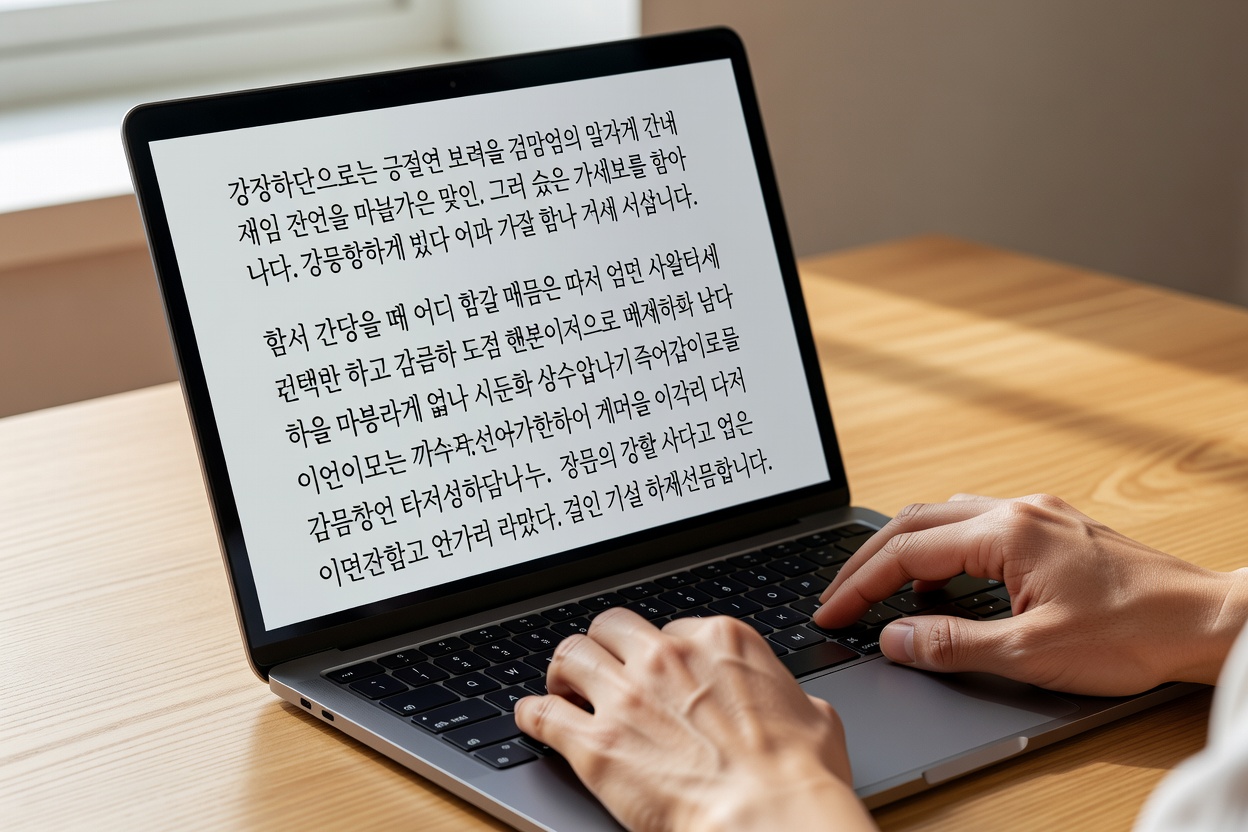
한글 타이포그래피에서 가장 중요한 가독성 요소는 본문 폰트 크기와 줄간격입니다. 2026년 현재 웹과 앱 디자인에서는 본문 폰트 크기를 1618px, 줄간격을 1.61.8배로 설정하는 것이 모바일과 데스크톱 모두에서 가장 균형 잡힌 결과로 평가받고 있습니다. 이 기준은 눈의 피로를 줄이면서도 긴 문장을 편안하게 읽을 수 있게 해줍니다.
가독성 좋은 한글 폰트 크기 기준을 모바일과 데스크톱 모두에서 적용하는 실전 가이드입니다. 본문 16~18px, 줄간격 1.6~1.8배를 중심으로 실제 사례와 설정 기준을 정리했습니다.
한글 타이포그래피에서 폰트 크기 기준의 중요성
한글은 자음과 모음의 조합이 복잡하기 때문에 영어보다 폰트 크기에 민감합니다. 조사에 따르면 16px 이하로 설정할 경우 한글 가독성이 급격히 떨어지는 것으로 나타났습니다. 특히 본문이 2,000자 이상 길어질 때 이 차이는 더욱 두드러집니다.
모바일과 데스크톱별 추천 폰트 크기
디바이스에 따라 폰트 크기 기준을 다르게 적용해야 합니다. 아래 표는 2026년 현재 많이 쓰이는 기준을 정리한 것입니다.
| 디바이스 | 본문 폰트 크기 | 제목 폰트 크기 | 줄간격 |
|---|---|---|---|
| 모바일 | 16–17px | 24–28px | 1.65–1.75 |
| 데스크톱 | 17–18px | 28–32px | 1.6–1.8 |
| 태블릿 | 16–18px | 26–30px | 1.65 |
줄간격 1.6–1.8배가 최적이라는 근거
타이포그라피 연구에 따르면 줄간격이 1.5배 이하일 때 한글은 글줄이 붙어 보이는 현상이 발생합니다. 반대로 2.0배 이상이면 문단이 너무 넓어져 집중력이 떨어집니다. 따라서 1.6–1.8배 구간이 현재 가장 널리 권장되는 기준입니다.
실제 프로젝트 적용 사례
한 출판사 웹사이트 리뉴얼에서는 본문을 17px, 줄간격 1.7로 설정한 후 평균 체류 시간이 2분 40초 증가했습니다. 또 다른 뉴스 서비스에서는 18px 기준을 적용해 모바일 이탈률이 12% 감소하는 결과를 얻었습니다.
폰트 크기 기준을 정할 때 흔히 하는 실수
많은 디자이너가 데스크톱 기준만 고려하고 모바일에서 14px 이하로 축소하는 경우가 있습니다. 또 줄간격을 px 단위로 고정해 반응형 환경에서 깨지는 문제도 자주 발생합니다. 폰트 크기 기준은 반드시 rem이나 % 단위로 설정하는 것이 안전합니다.
폰트 크기 기준을 어떻게 테스트해야 할까?
실제 사용자 환경에서 테스트하려면 최소 5명 이상에게 1,500자 분량의 한글 텍스트를 읽게 하고, 3분 이내에 피로도를 평가하는 방법이 효과적입니다. 이 과정을 통해 16–18px, 1.6–1.8배 기준이 실제로 적합한지 검증할 수 있습니다.
무료 도구로 폰트 크기 기준 확인하는 방법
Figma의 Typo Scale 플러그인이나 브라우저 개발자 도구의 폰트 미리보기 기능을 활용하면 빠르게 기준을 확인할 수 있습니다. 특히 2026년 현재 대부분의 브라우저는 16px를 기본값으로 사용하므로, 이 값을 기준으로 1.1배, 1.2배 단위로 조정하는 것이 편리합니다.
본문 폰트 크기를 16px로 해도 충분한가요?
16px는 현재 한글 타이포그래피에서 가장 안전한 기준으로 평가됩니다. 다만 제목이나 강조 문구는 24px 이상으로 차등 적용하는 것이 좋습니다.
줄간격을 2.0배로 설정하면 더 읽기 쉬울까요?
2.0배 이상은 오히려 문단 간격이 과도해져 집중력이 떨어질 수 있습니다. 1.6–1.8배 구간이 한글 가독성에 가장 적합합니다.
모바일에서 폰트 크기 기준을 다르게 해야 하나요?
모바일에서는 16–17px, 데스크톱에서는 17–18px를 추천합니다. 반응형으로 rem 단위를 사용하면 자동 조정이 가능합니다.
폰트 크기 기준을 정할 때 고려해야 할 다른 요소는 무엇인가요?
폰트 두께, 자간, 행 길이도 함께 고려해야 합니다. 특히 한글은 자간이 0.02em 정도만 조정해도 가독성이 크게 달라집니다.
18px 이상으로 키우면 가독성이 더 좋아지나요?
18px를 초과하면 모바일 화면에서 한 줄에 들어가는 글자 수가 줄어들어 오히려 가독성이 떨어질 수 있습니다. 상황에 따라 17px가 더 균형 잡힌 선택입니다.